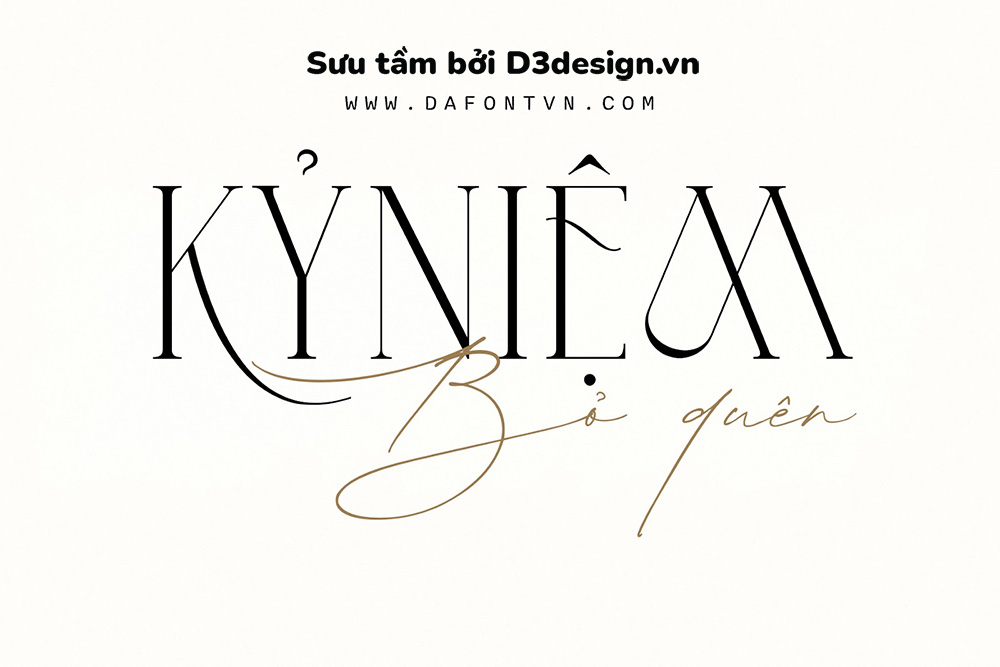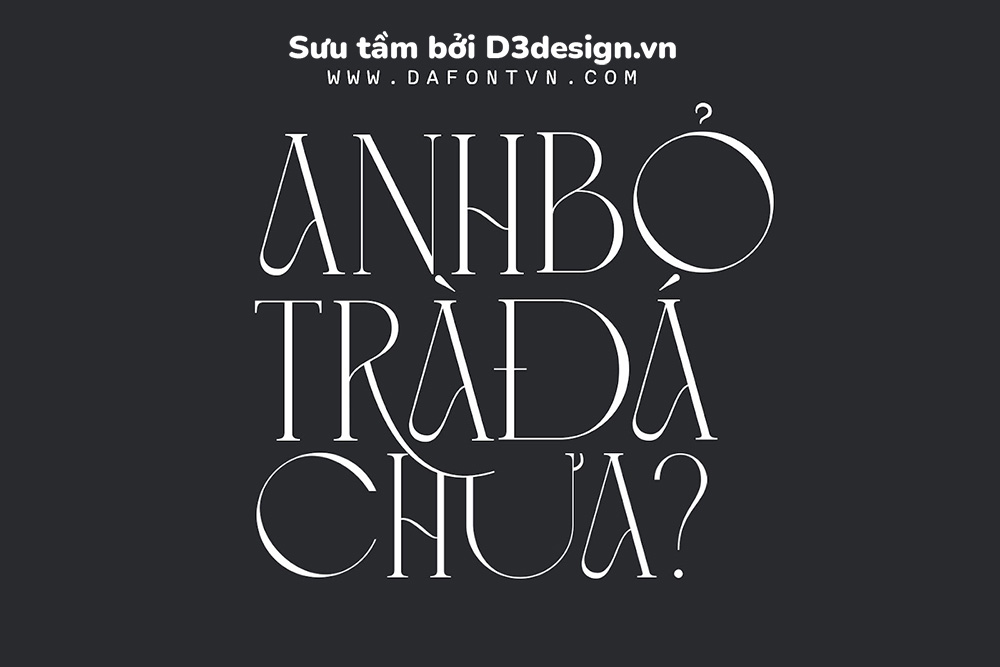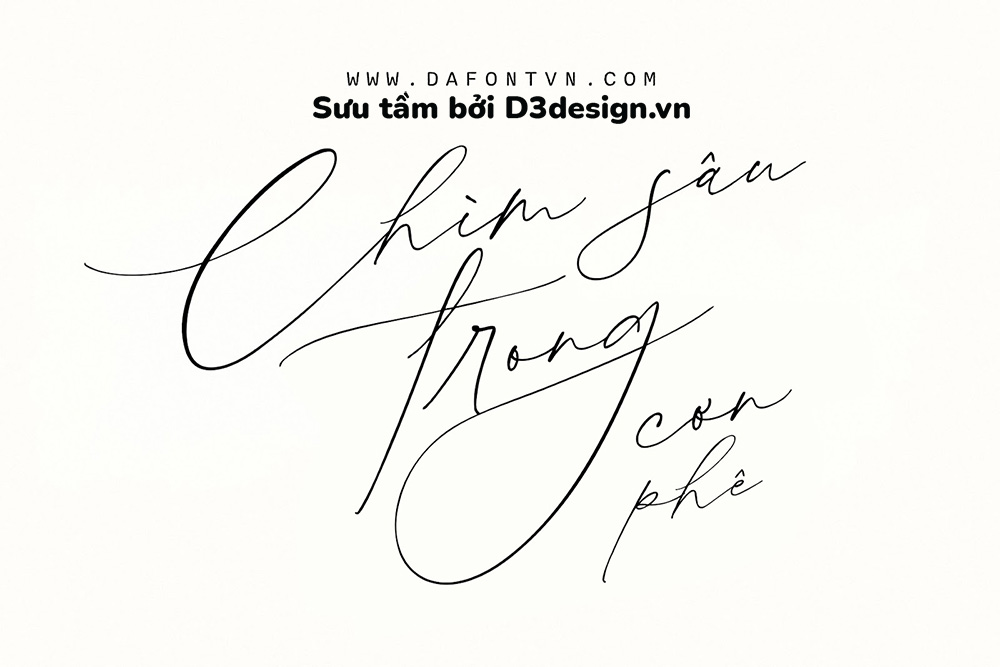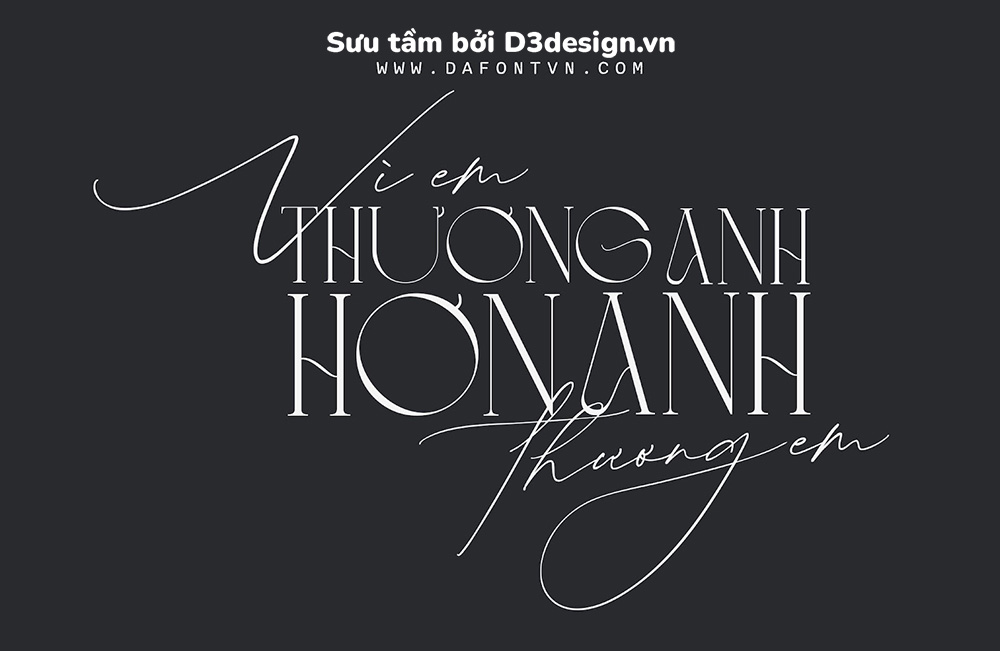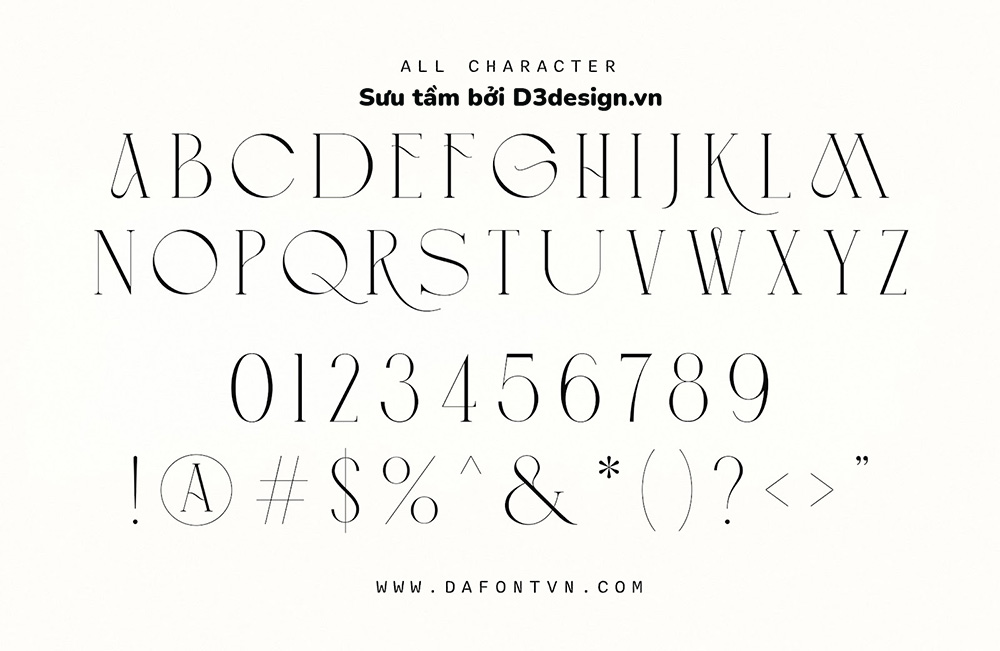
Font Việt Hóa - Simple Serenity (Font Đôi) Mang Phong Cách Hiện Đại Và Cổ Điển
Giới thiệu bộ đôi Font Simple Serenity. Bộ đôi font tuyệt đẹp này là sự kết hợp nét hiện đại của serif cổ điển và kiểu chữ viết tay ấn tượng - tạo ra cặp đôi hoàn hảo tuyệt đẹp phù hợp cho nhiều thiết kế khác nhau như xây dựng thương hiệu, thiệp mời, thiệp đám cưới, quotes, typography, văn bản hiển thị...
Việt hóa đầy đủ 2 font bao gồm:
- Simple Serenity Script: Phông chữ viết tay hiện đại với các nét chữ được thiết kế tỉ mỉ, các ký tự viết hoa và viết thường chất lượng, đi kèm với 50 chữ ghép để giúp thiết kế của bạn ấn tượng hơn.
- Simple Serenity Serif: Phông chữ serif hiện đại mang phong cách cổ điển. Các ký tự chỉ viết hoa và bao gồm 14 chữ ghép độc đáo và tinh tế.
Cả 2 font chữ đều chứa một số "Standard Ligatures" (Tiêu chuẩn chữ ghép) và "Stylistic Alternates" (Kiểu chữ thay thế) để cung cấp cho bạn nhiều tùy chọn tùy chỉnh hơn thông qua bảng Glyphs.
Bộ đôi font Simple Serenity được việt hóa đầy đủ, kerning lại, chỉnh sửa, tối ưu cũng như được mã hóa PUA để bạn có thể sử dụng dễ dàng trên bất kỳ phần mềm nào.